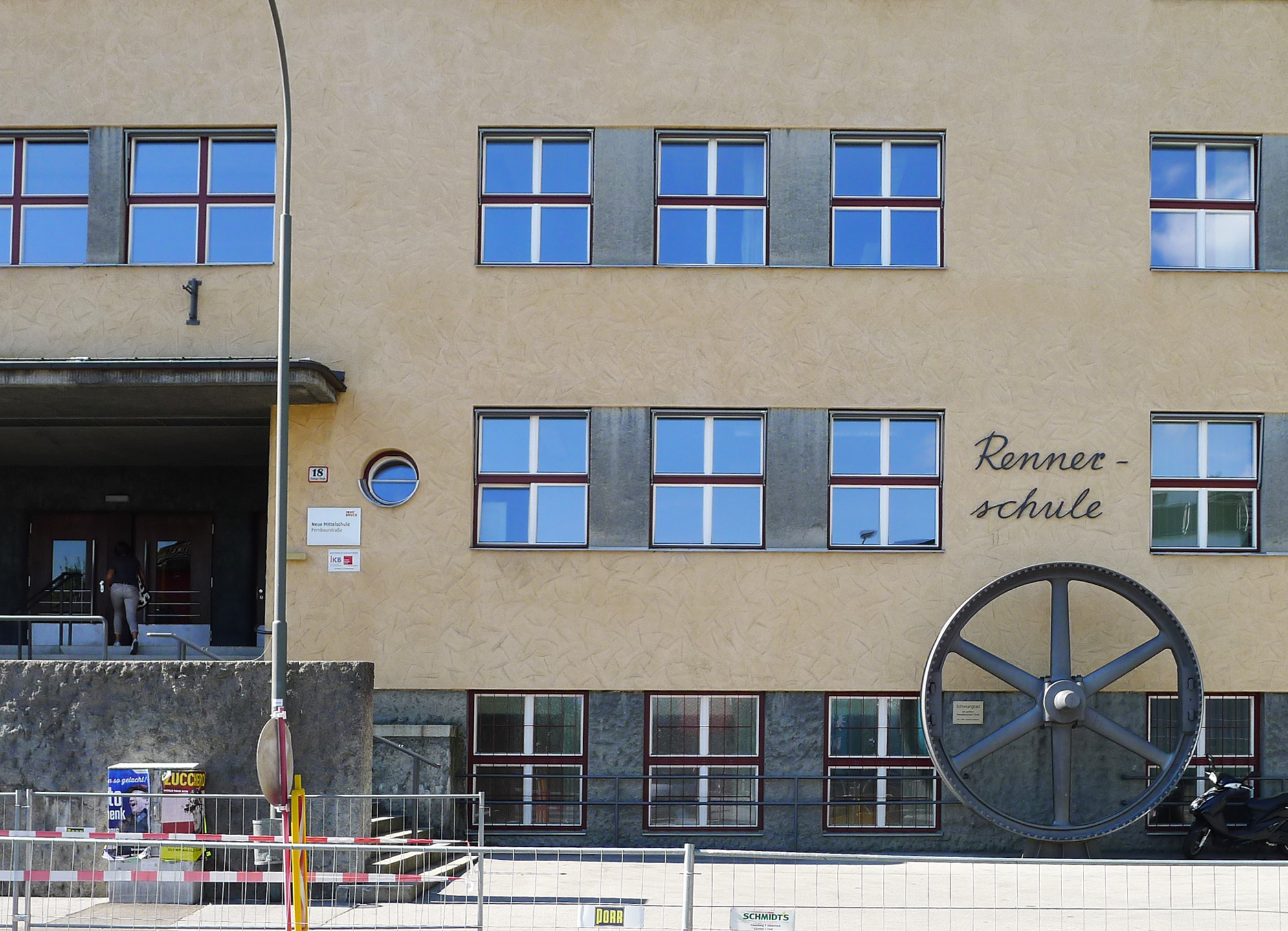
Rennerschule
Der bekannte Tiroler Architekt Theodor Prachensky (der auch Maler war) hat 1928–1936 diese Schule gebaut, die heute "Pembauerstraße" heißt. In ihrer klaren Strenge ein schönes Beispiel für die Tiroler Moderne. Das Schwungrad der größten Dampfmaschine Tirols erhielt die Schule 1997 als Wahrzeichen. Die geschwungene Schrift aus Stahl sieht eher nach den 1950er Jahren aus, auf den Originalplänen von Prachensky ist sie jedenfalls noch nicht zu sehen.